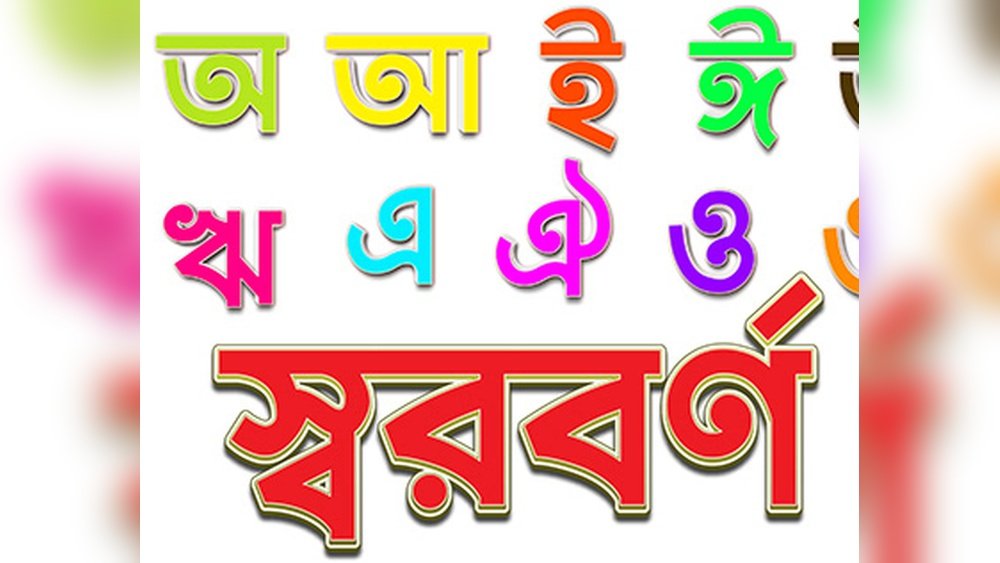
আপনি কি আপনার ডিজাইন বা লেখার কাজে এমন একটি বাংলা ফন্ট খুঁজছেন যা দেখতে সুন্দর, স্পষ্ট এবং সহজে পড়া যায়? তাহলে Bornomala Bangla Font আপনার জন্য একদম পারফেক্ট চয়েস হতে পারে। এই ফন্টটি শুধু আপনার লেখাকে আরও আকর্ষণীয় করে তুলবে না, বরং আপনার প্রেজেন্টেশন, ব্লগ, বা যেকোনো ডিজিটাল প্রজেক্টকে এক নতুন লেভেলে নিয়ে যাবে। আপনি কি জানেন, সঠিক ফন্ট ব্যবহারে আপনার পাঠকের নজর কাড়ে এবং তারা আপনার লেখা আরও মনোযোগ দিয়ে পড়ে?
Bornomala Bangla Font: পরিচিতি ও উদ্দেশ্য
Bornomala Bangla Font হলো একটি ইউনিক বাংলা ফন্ট যা বাংলা লিপির সৌন্দর্য ও পাঠযোগ্যতা বাড়ায়। এটি ডিজাইন করা হয়েছে সহজ, পরিষ্কার এবং আকর্ষণীয় লেখার জন্য। ফন্টটি বাংলা ভাষাভাষীদের জন্য আধুনিক ও প্রফেশনাল লেখনী তৈরিতে বিশেষ সহায়ক।
এই ফন্টটি বাংলা বর্ণমালা ও শব্দের স্পষ্টতা বজায় রেখে ডিজাইন করা হয়েছে। ফলে এটি বিভিন্ন ডিজিটাল ও প্রিন্ট মিডিয়ায় ব্যবহার উপযোগী। এই ফন্টের মাধ্যমে বাংলা লেখার অভিজ্ঞতা নতুন মাত্রা পায়।
Bornomala Bangla Font কি এবং এর প্রয়োজনীয়তা
Bornomala Bangla Font একটি ইউনিকোড ফন্ট যা বাংলা ভাষার সমস্ত বর্ণকে সুন্দরভাবে উপস্থাপন করে।
- বাংলা লেখার জন্য পরিষ্কার ও সহজ ফন্টের প্রয়োজন আছে।
- ডিজিটাল প্ল্যাটফর্মে বাংলা লেখাকে আরও আকর্ষণীয় করতে সাহায্য করে।
- শিক্ষা, প্রকাশনা, ও বিজ্ঞাপনে বাংলা ফন্টের মান উন্নত করে।
- বিভিন্ন ডিভাইসে সমানভাবে পড়া যায় এমন ফন্টের প্রয়োজনীয়তা পূরণ করে।
ফন্টটি ব্যক্তিগত ও ব্যবসায়িক কাজে ব্যবহার উপযোগী। এতে বাংলা লিপির ঐতিহ্য ও আধুনিকতার সমন্বয় দেখা যায়।
বাংলা লিপিতে নতুন অভিজ্ঞতার সূচনা
Bornomala Bangla Font নতুন ধরনের লেখনী পরিবেশ তৈরিতে সহায়তা করে।
- বাংলা ভাষার পাঠযোগ্যতা বৃদ্ধি করে।
- লেখার সৌন্দর্য ও প্রফেশনালিজম বাড়ায়।
- ডিজিটাল মিডিয়ায় বাংলা লিপির ব্যবহার সহজ ও আনন্দদায়ক করে তোলে।
- বিভিন্ন ডিজাইন ও প্রকাশনায় সৃজনশীলতার সুযোগ দেয়।
ফন্টটি ব্যবহার করে বাংলা লেখায় নতুনত্ব ও প্রাণবন্ততা আনা যায়। এটি লেখকদের ও ডিজাইনারদের জন্য একটি কার্যকর হাতিয়ার।
Bornomala Bangla Font-এর বিশেষ বৈশিষ্ট্য
Bornomala Bangla Font একটি আধুনিক এবং ব্যবহারবান্ধব বাংলা ফন্ট। এটি ডিজাইন ও প্রযুক্তির সমন্বয়ে তৈরি। বাংলা লেখার জন্য এটি সহজ, স্পষ্ট এবং সুন্দর। ফন্টটির বৈশিষ্ট্যগুলি বিভিন্ন ডিজাইন ও লেখালেখিতে উপযোগী।
বাংলা ভাষাভাষীদের জন্য এটি একটি আদর্শ ফন্ট। কারণ এর ইউনিকোড সমর্থন, পাঠযোগ্যতা এবং প্ল্যাটফর্ম সামঞ্জস্য খুব ভালো। নিচে Bornomala Bangla Font-এর মূল বৈশিষ্ট্যগুলো বিস্তারিতভাবে তুলে ধরা হল।
ইউনিকোড সমর্থন ও বহুমুখী ব্যবহার
Bornomala Bangla Font সম্পূর্ণ ইউনিকোড সমর্থিত। এর মানে, ফন্টটি সর্বাধুনিক বাংলা লেখার স্ট্যান্ডার্ড অনুসরণ করে।
ইউনিকোড সমর্থনের কারণে কোনও অক্ষর মিস হয় না। এটি বাংলা লেখার ক্ষেত্রে নির্ভরযোগ্যতা বাড়ায়।
সহজ এবং স্পষ্ট ডিজাইন যা পড়তে সহজ
ফন্টটির ডিজাইন অত্যন্ত পরিষ্কার এবং সহজ। প্রতিটি অক্ষর স্পষ্ট এবং চোখে আরামদায়ক।
- লেখা পড়তে সুবিধাজনক।
- দীর্ঘ সময় পড়লেও চোখে চাপ দেয় না।
- শিক্ষার্থী থেকে পেশাদার সবাই ব্যবহার করতে পারে।
এই সহজ এবং স্পষ্ট ডিজাইন বাংলা লেখাকে সুন্দর করে তোলে।
বিভিন্ন প্ল্যাটফর্মে সামঞ্জস্যপূর্ণতা
| লিনাক্স | পূর্ণ | ওপেন সোর্স সফটওয়্যারে সমর্থিত |
| ওয়েব | পূর্ণ | ওয়েব ডিজাইন ও অনলাইন প্রকাশে ব্যবহারযোগ্য |
মাত্রালতার সুবিধা ও টাইপোগ্রাফিক নিয়ন্ত্রণ
ফন্টটি বিভিন্ন মাত্রায় পাওয়া যায়। এটি টাইপোগ্রাফিক নিয়ন্ত্রণ সহজ করে।
- বিভিন্ন ওজন (Weight) যেমন: নিয়মিত, বোল্ড ইত্যাদি।
- টেক্সটের আকার ও ঘনত্ব নিয়ন্ত্রণে সহায়ক।
- ডিজাইনাররা সহজেই পছন্দমতো সামঞ্জস্য করতে পারেন।
এটি প্রিন্ট ও ডিজিটাল উভয় মাধ্যমেই ভালো ফল দেয়।
মূল্য নির্ধারণ এবং প্রাপ্যতা
Bornomala Bangla Font বাংলা ফন্টের মধ্যে একটি জনপ্রিয় ফন্ট। এর মূল্য নির্ধারণ এবং প্রাপ্যতা অনেকের জন্য গুরুত্বপূর্ণ বিষয়। ফন্টটি সহজেই পাওয়া যায় এবং মূল্য নির্ধারণের ক্ষেত্রে বেশ নমনীয়।
ফ্রি এবং ওপেন সোর্স হিসেবে পাওয়া যায়
Bornomala Bangla Font ফ্রি এবং ওপেন সোর্স হিসেবে পাওয়া যায়। অর্থাৎ, কোনো খরচ ছাড়াই ব্যবহার করতে পারেন।
- ফন্টটি সম্পূর্ণ ইউনিকোড সমর্থিত।
- বিনামূল্যে ডাউনলোড ও ব্যবহার সম্ভব।
- সোর্স কোড ও ফন্ট ফাইল উন্মুক্ত।
এই ফ্রি ফিচারটি শিক্ষার্থী, ডিজাইনার ও ব্লগারদের জন্য বিশেষ সুবিধাজনক।
বর্ণমালা ফন্ট কি সকল ডিভাইসে কাজ করে?
হ্যাঁ, বর্ণমালা বাংলা ফন্ট উইন্ডোজ, ম্যাক, অ্যান্ড্রয়েড ও আইওএস সহ সকল প্রধান প্ল্যাটফর্মে সমর্থিত। তাই আপনি যেকোনো ডিভাইসে সহজেই ব্যবহার করতে পারবেন।
Conclusion
বর্ণমালা বাংলা ফন্ট বাংলা লেখাকে সহজ ও সুন্দর করে তোলে। এই ফন্টটি ব্যবহার করে আপনি পেশাদার ডিজাইন তৈরি করতে পারবেন। এটি বিভিন্ন প্রজেক্টে কাজে আসবে। Bornomala Bangla Font থেকে সহজেই ডাউনলোড করুন। ফন্টটির ব্যবহার খুবই সোজা এবং স্পষ্ট। বাংলা ভাষার প্রতি ভালোবাসা বাড়াতে এটি আদর্শ। নতুন ডিজাইন বা লেখায় বর্ণমালা ফন্টের জাদু মিশিয়ে নিন। আপনার কাজ হবে আরো আকর্ষণীয় ও পেশাদার।